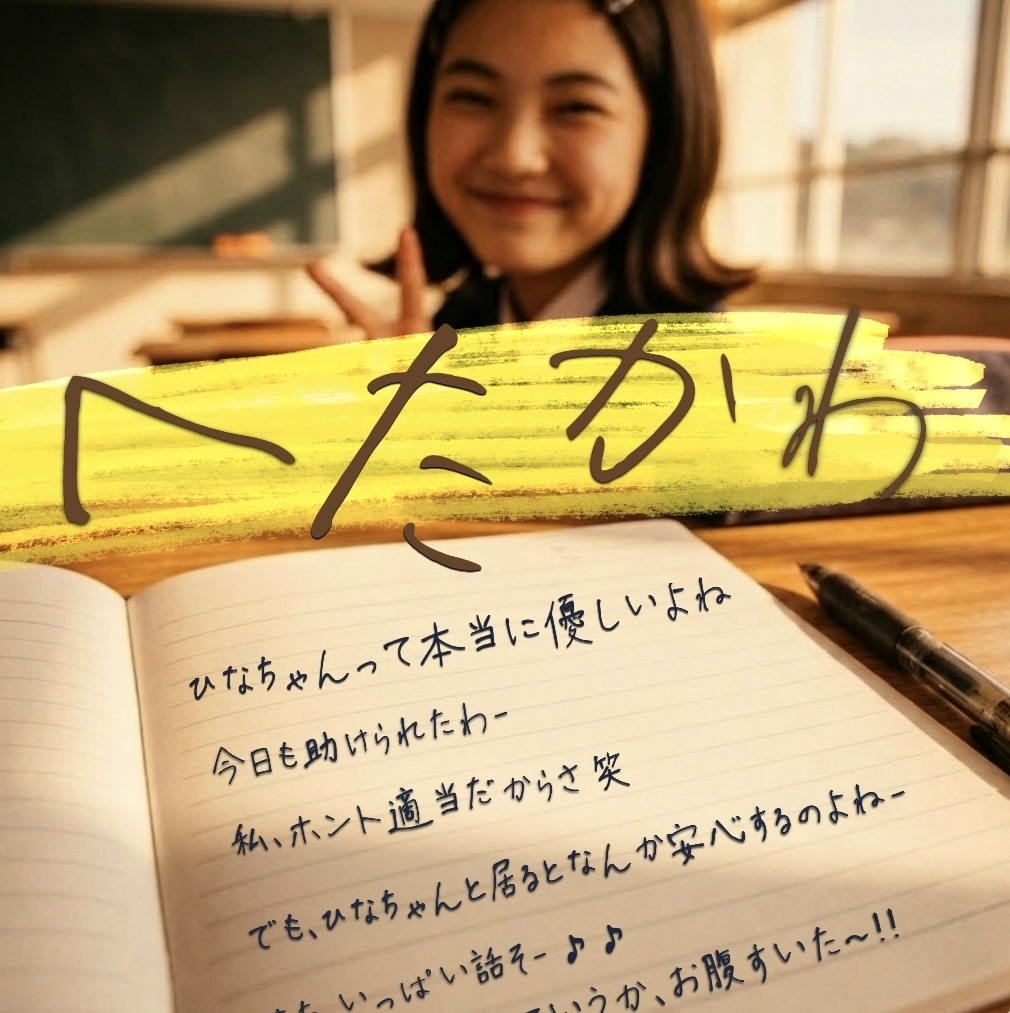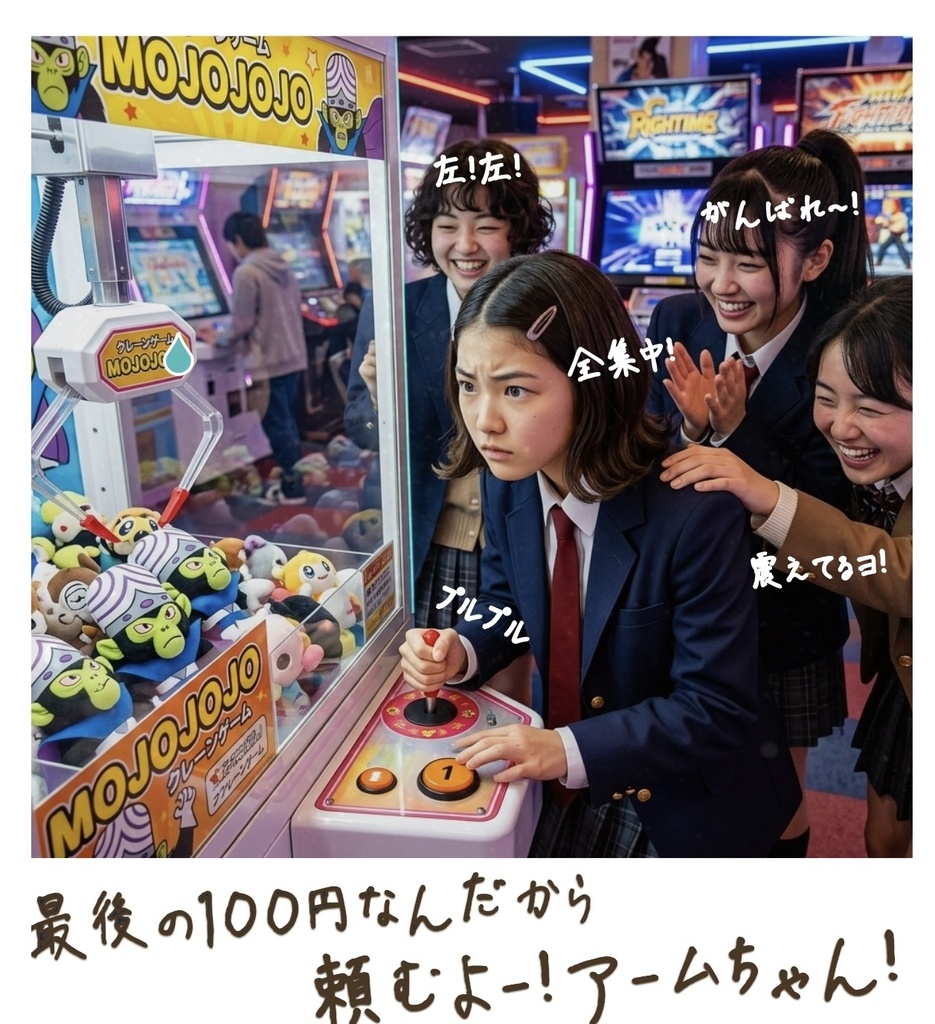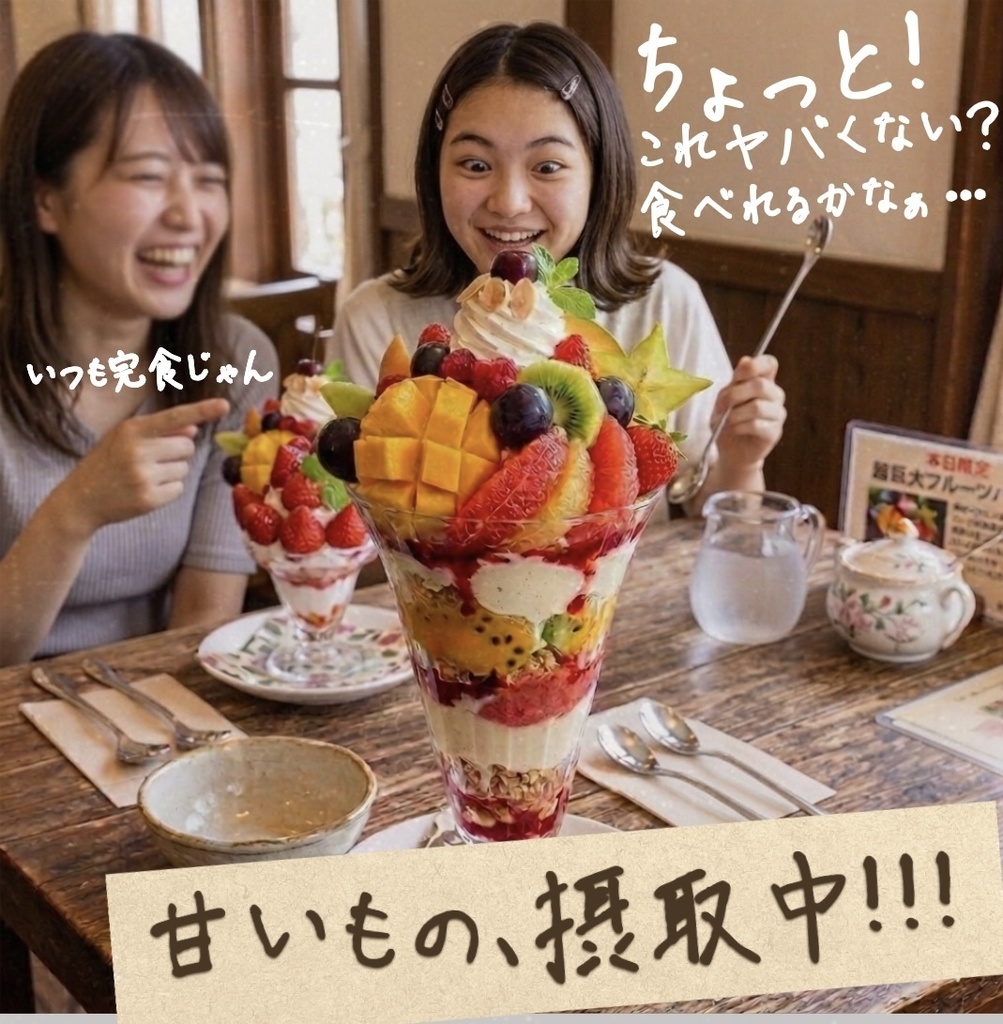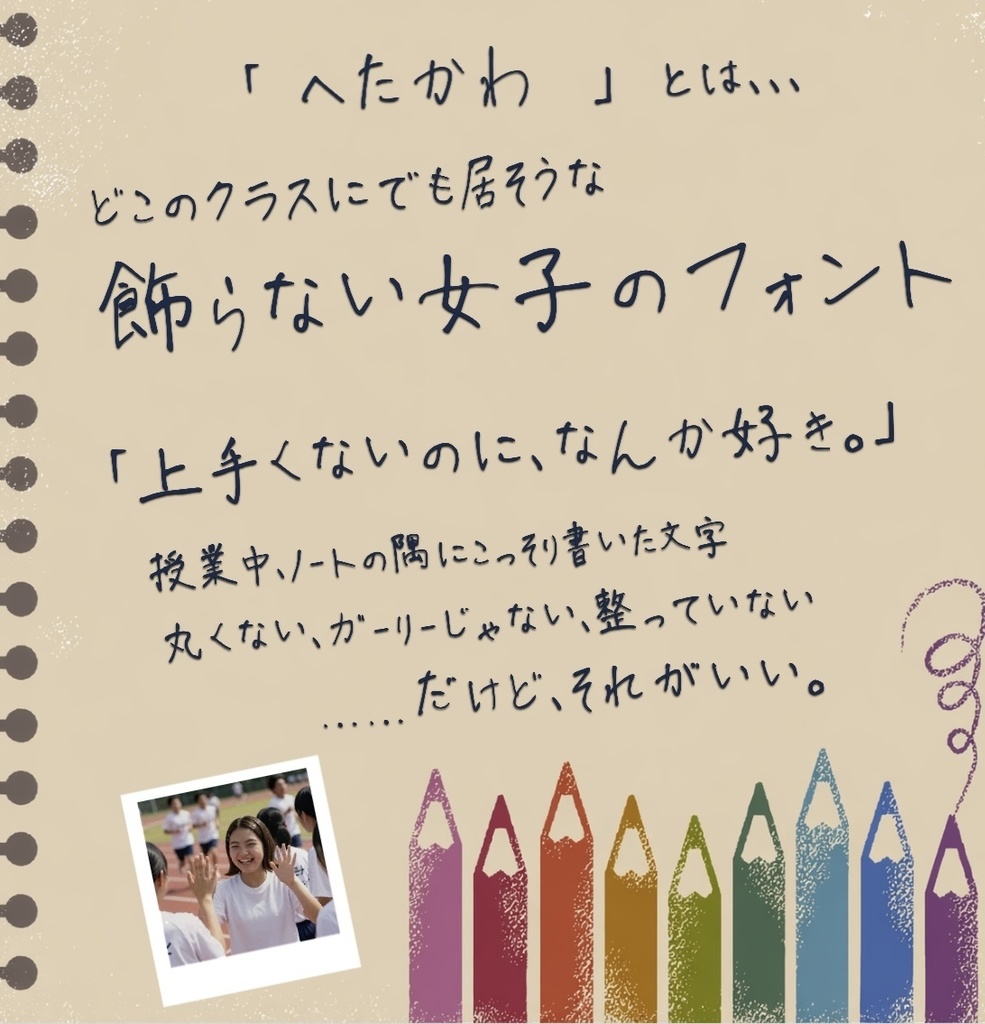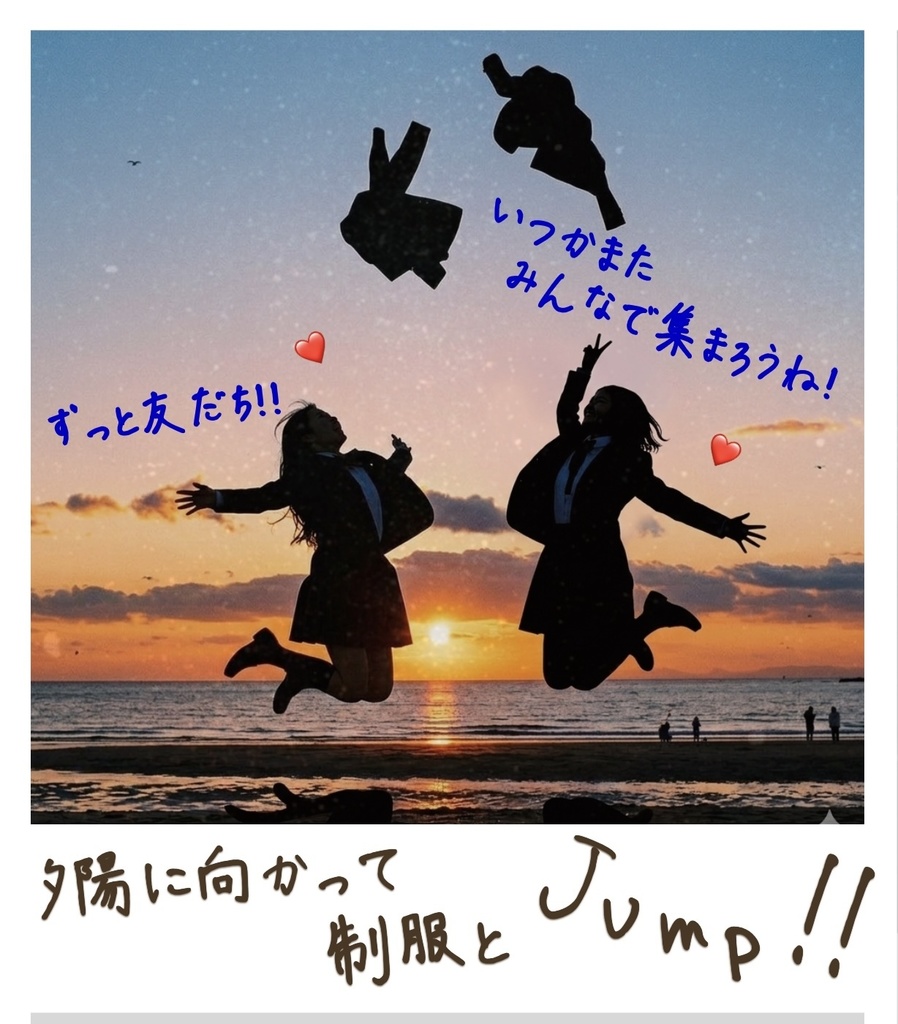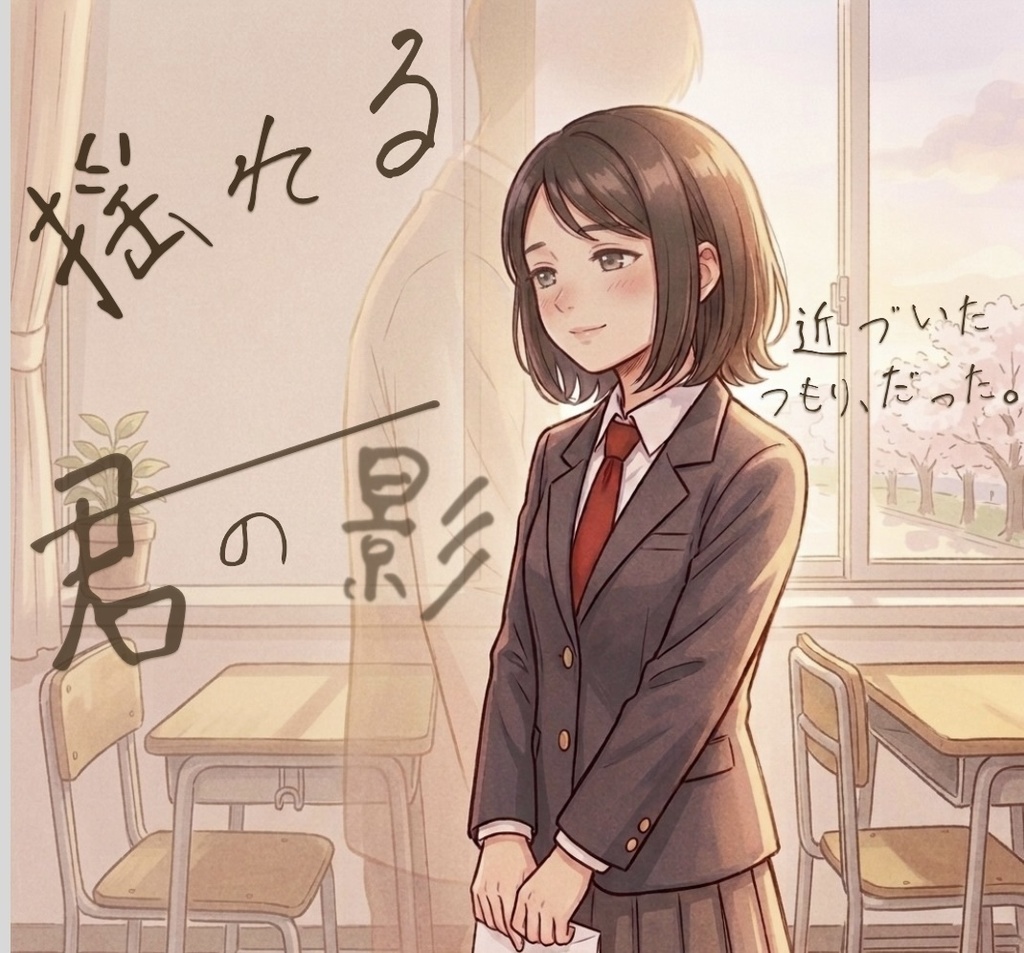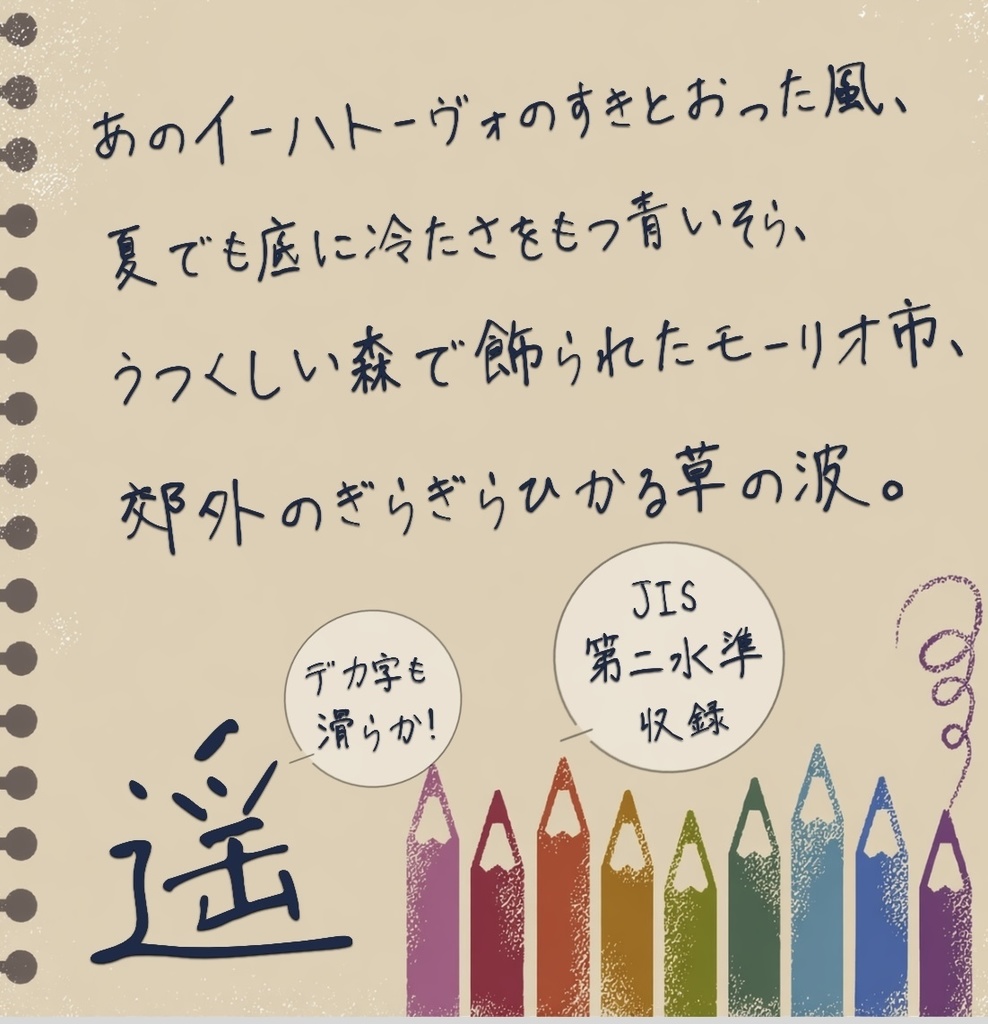
【フリー版有/商用可】手書きフォント「へたかわ hetakawa」【リアル女子手書き】
■おかげ様で 累計ダウンロード数が400を越えました。 又、多くの方から推薦を頂きました。ありがとうございます。 いいフォントさんにご紹介頂きました https://goodfreefonts.com/10948/ コリスさんにご紹介頂きました https://coliss.com/articles/freebies/japanese-free-fonts.html ■コンセプト 「不完全な個性」 AIデザインの普及により、画一的な表現があふれる今。「へたかわ」は、"飾らない女子"の手書きフォントが持つ不完全さを、むしろ個性として昇華。素朴なアマチュア感が、ユーザーの心をつかみます。 ■特徴 一般的な女子系手書きフォントといえば、丸文字・ガーリー・綺麗系が定番。しかし「へたかわ」は、クラスの主役ではない"普通の女子"の手書きをモチーフにしています。その素朴でリアルな雰囲気が、言葉やコメントに自然な共感を生み出します。 また、文字のサイズやバランスにあえて"ばらつき"を持たせることで、人の温もりをダイレクトに伝えられるのも大きな特徴です。女子系フォントでありながら、どこか手放しに信頼できる温度感があります。 大きくしても、ずっと滑らか: どれだけ引き伸ばしてもガビガビしない高品質なアウトライン設計。同人誌の表紙、ポスター等、大画面での使用も可能です。 ■ 有料版について 女子系にしては珍しく、豊富な文字を揃えており JIS第二水準までの漢字(約6,900文字)を収録。 「この漢字、ない…」で困る事は無いです。 ■ メッセージ AIにはだせない"普通の温度"。へたかわが、あなたの言葉をリアルにします。